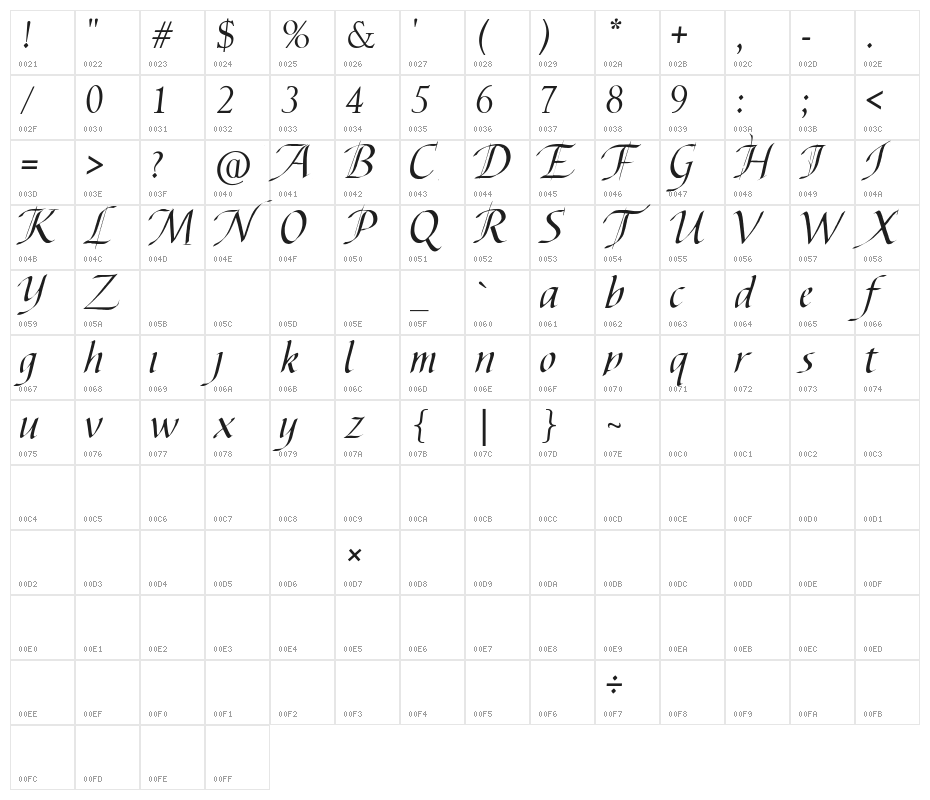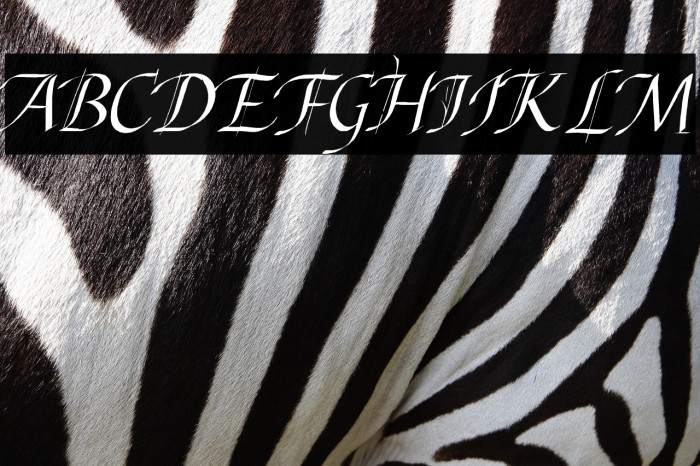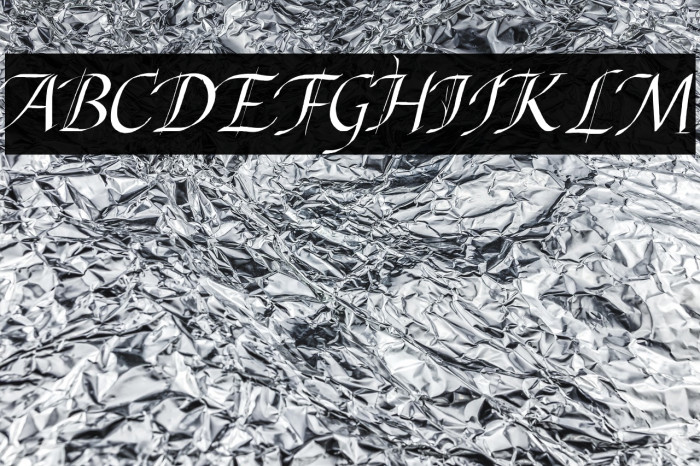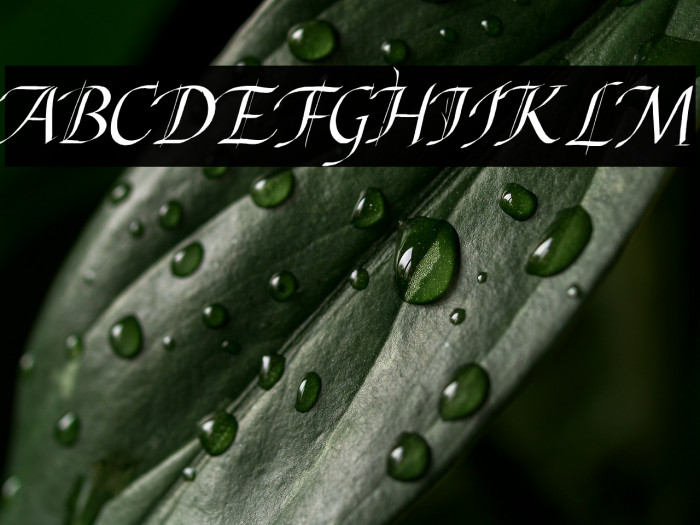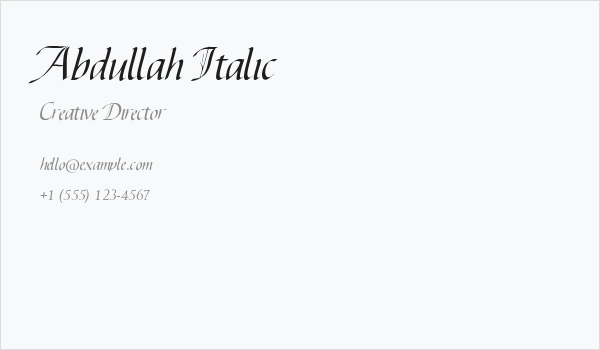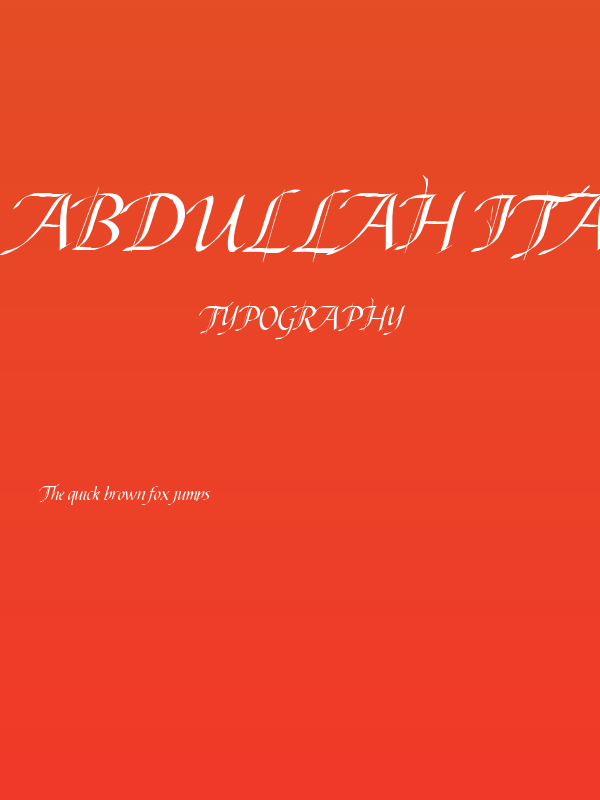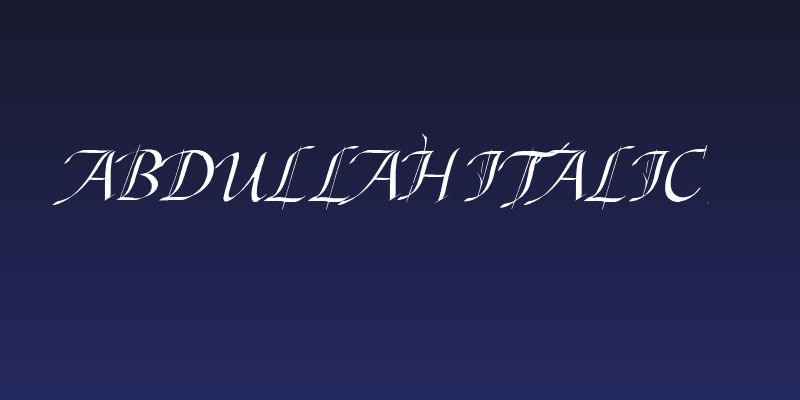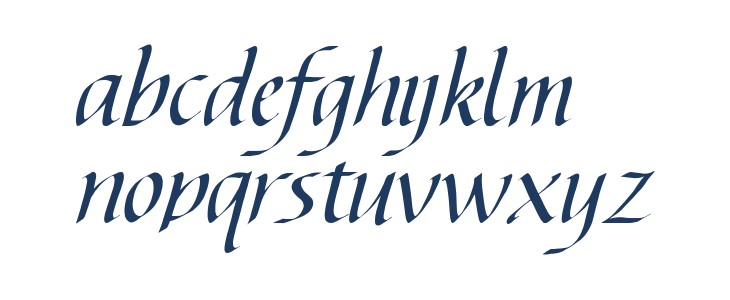
Abdullah Italic Font
| Stile generale | Elegant, Sophisticated |
| Caso d'uso | Headlines, Invitations, Branding |
| Progetti proposti | Ideal for wedding invitations, luxury branding, editorial design, and elegant packaging. |